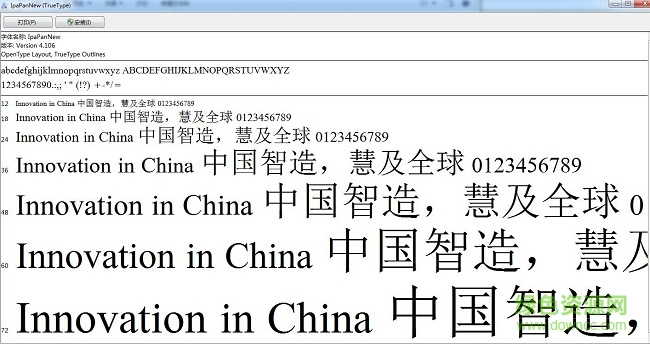
用音標(biāo)標(biāo)記語(yǔ)音的方法叫標(biāo)音法。一般分為嚴(yán)式標(biāo)音法和寬式標(biāo)音法兩種。
【寬式標(biāo)音】
所謂寬式標(biāo)音,是在嚴(yán)式標(biāo)音的基礎(chǔ)上,整理出一種語(yǔ)音的音位系統(tǒng),然后按音位來(lái)標(biāo)記語(yǔ)音,也就是只記音位,不記音位變體及其它非本質(zhì)的伴隨現(xiàn)象。因此,寬式標(biāo)音又稱(chēng)為“音位標(biāo)音”。
【嚴(yán)式標(biāo)音】
所謂嚴(yán)式標(biāo)音,就是出現(xiàn)什么音素就記錄什么音素,有什么伴隨現(xiàn)象就記錄什么伴隨現(xiàn)象。無(wú)論什么音素和什么伴隨現(xiàn)象都不放過(guò),也就是最忠實(shí)、最細(xì)致的記錄語(yǔ)音的原貌。所以,嚴(yán)式標(biāo)音又稱(chēng)為“音素標(biāo)音”。